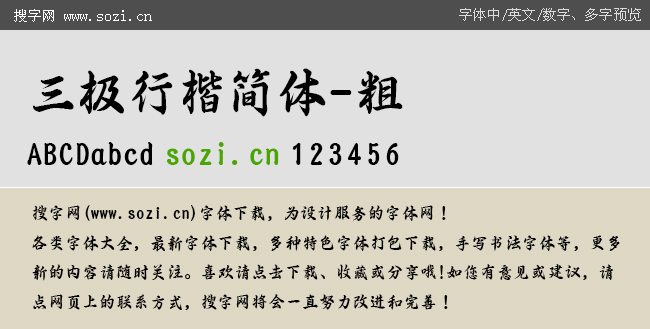
三極行楷簡體-粗
搜字網(wǎng)給大家提供一三極行楷簡體-粗中文字體下載,三極行楷簡體是一款手寫風(fēng)格的行楷字體,字體瀟灑大方,視覺效果非常不錯。適用于平面宣傳設(shè)計(jì)、網(wǎng)頁設(shè)計(jì)、海報(bào)設(shè)計(jì)等應(yīng)用。
• 風(fēng)格類別: 行楷